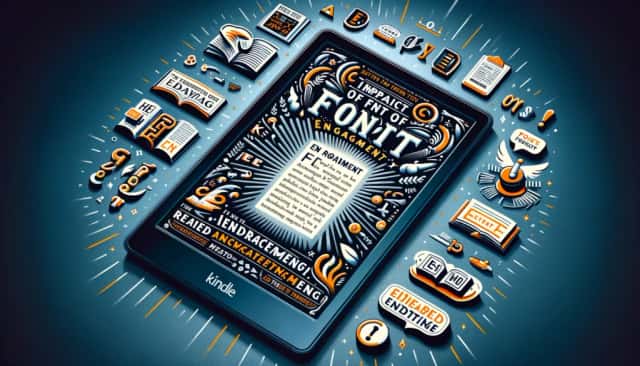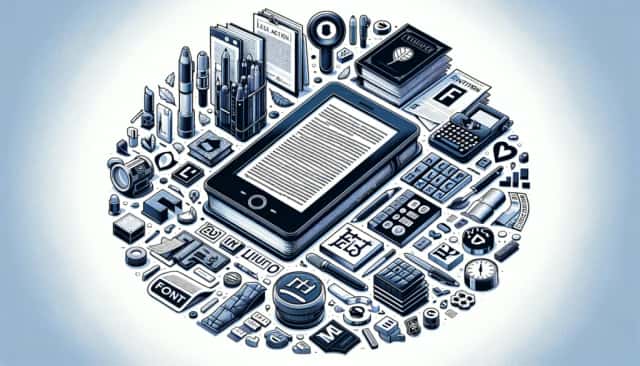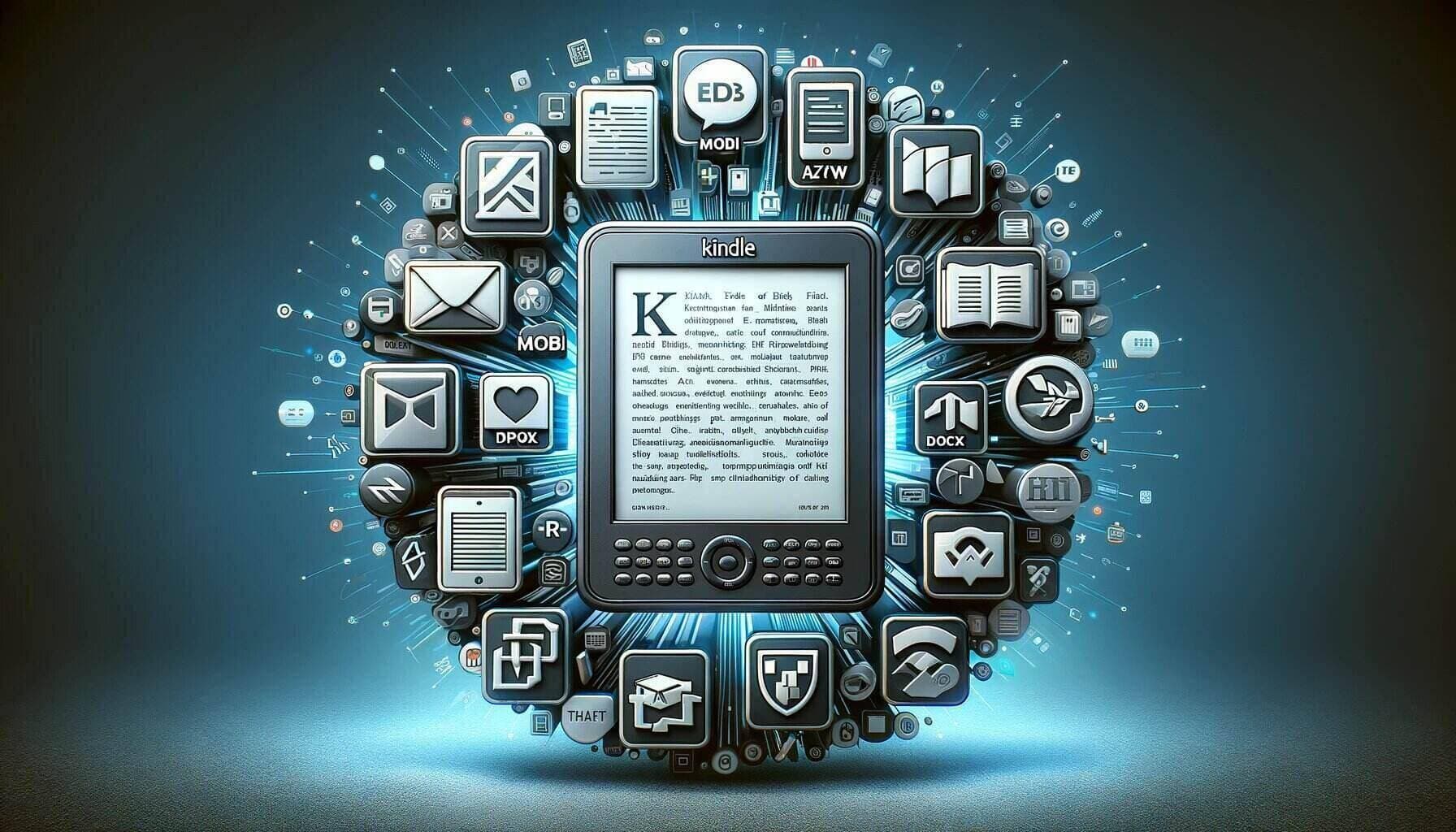
Hast du jemals darüber nachgedacht, wie die beste Schriftart für Kindle dein Leseerlebnis erheblich beeinflussen kann? Es ist etwas, dem nicht viel Beachtung geschenkt wird, aber glaub mir, es ist bahnbrechend. Die Wahl der richtigen Schriftart geht nicht nur um Ästhetik; sie geht um Komfort, Lesbarkeit und darum, dass deine Augen nicht zu schnell ermüden.
Wenn du die perfekte Schriftart findest, scheint es, als würden die Wörter einfach fließender fließen, wodurch deine Lesesitzungen noch angenehmer werden. Und wenn du für Kindle schreibst und veröffentlichst, wird diese Wahl noch entscheidender. Du willst, dass deine Leser ohne Anstrengung in deine Geschichten eintauchen, gefesselt und bequem bleiben.
Also lass uns herausarbeiten, warum die Wahl der perfekten Schriftart wichtig ist und wie sie dein Kindle-Erlebnis sowie das deiner Leser verstärken kann. Stell es dir als eine von diesen kleinen Anpassungen vor, die große Vorteile bringen – etwas, von dem ich mir gewünscht hätte, es zu wissen, als ich meine Kindle-Reise begann.
Beste Schriftart für Kindle
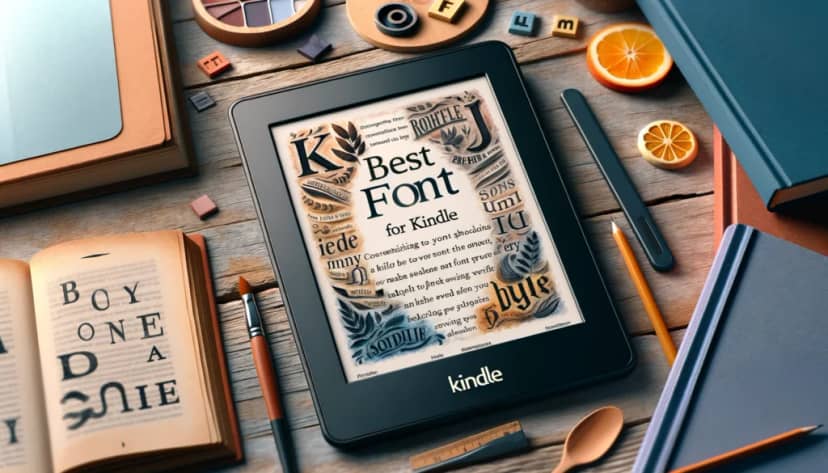
Die Wahl der besten Schriftart mag trivial klingen, doch sie ist mehr als nur das Aussehen der Buchstaben. Denken wir kurz darüber nach, warum die Schriftart wichtig ist, und schauen uns dann einige der beliebtesten Optionen an.
Warum die Schriftart beim Kindle-Lesen wichtig ist
Zuerst lass uns über Komfort sprechen. Das Lesen auf einem digitalen Bildschirm ist nicht dasselbe wie das Umblättern durch die Seiten eines Taschenbuchs. Unsere Augen arbeiten anders, wenn wir auf einen beleuchteten Hintergrund starren.
Hier kommt eine gute Schrift ins Spiel. Die richtige Schrift kann die Augenbelastung verringern und es dir leichter machen, dich stundenlang in ein Buch zu vertiefen, ohne das Gefühl zu haben, dass deine Augen gleich protestieren.
Dann kommt die Frage der Lesbarkeit. Nicht alle Schriftarten sind gleich geschaffen – manche sehen auf einer Seite hübsch aus, können aber zu einem kleinen Albtraum werden, wenn man ihnen Zeile für Zeile auf dem Bildschirm folgen möchte.
Kindle-Bildschirme sind ziemlich gut, aber sie sind nicht perfekt, und manche Schriftarten funktionieren in dieser digitalen Umgebung einfach besser. Sie helfen, den Text klar und scharf zu machen, sodass du nicht zusammenkneifen oder die Helligkeit alle paar Minuten anpassen musst.
Und hier ist etwas, das nicht jeder in Betracht zieht – die Stimmung. Ja, Schriftarten tragen eine Atmosphäre in sich! Denke darüber nach: Ein Thriller wirkt vielleicht nicht so bedrückend in einer Comic Sans-ähnlichen Schrift, oder?
Deine Schriftwahl kann tatsächlich den Ton deines Buches ergänzen und dem Leser eine zusätzliche Atmosphäre hinzufügen.
Wenn du durch die Schriftoptionen auf deinem Kindle scrollst oder dein Manuskript für die Veröffentlichung vorbereitest, erinnere dich daran, dass es nicht nur eine triviale Entscheidung ist. Es geht darum, dein Lese- oder Schreiberlebnis so angenehm und effektiv wie möglich zu gestalten. Glaub mir: Sobald du anfängst, darauf zu achten, wirst du sehen, dass es wirklich eine echte Veränderung ist!
Beliebte Schriftarten für Kindle
Bevor man sich in bestimmte Schriftarten vertieft, ist es hilfreich zu wissen, dass es zwei Haupttypen gibt: Serif und Sans Serif.
Serif-Schriften haben kleine Linien an den Enden der Buchstaben und vermitteln ein traditionelles Erscheinungsbild. Sans-Serif-Schriften, denen diese Linien fehlen, wirken sauberer und moderner.
Beide Typen haben ihre Vorteile beim Kindle-Lesen.
Serif-Schriften
Serif-Schriften werden oft mit Komfort und Leichtigkeit beim Lesen längerer Texte in Verbindung gebracht, dank ihres traditionellen Erscheinungsbildes und der Art, wie die Serifen das Auge des Lesers von einem Wort zum nächsten führen.
- Bookerly: Amazons eigene Kreation, speziell für Kindle-Geräte entwickelt, und bietet eine optimale Balance zwischen Ästhetik und Lesbarkeit.
- Georgia: Bekannt für ihre Lesbarkeit auf Bildschirmen, Georgia verfügt über eine großzügige x-Höhe, was sie auch bei kleineren Größen klar und gut lesbar macht.
- Times New Roman: Eine klassische Schriftart, die zwar traditioneller ist, vielen Lesern aber vertraut ist und bequem auf Kindle-Geräten verwendet werden kann.
Sans-Serif-Schriften
Sans-Serif-Schriften sind typischerweise leichter für die Augen beim Lesen am Bildschirm und bieten ein geradliniges, sauberes Erscheinungsbild, das die Augenbelastung minimiert.
- Verdana: Entwickelt mit dem Lesen auf dem Bildschirm im Sinn; seine breiten Buchstaben und großzügige Abstände machen es zu einer soliden Wahl für Kindle-Nutzer.
- Arial: Bekannt für Klarheit und Einfachheit, ist Arial eine vielseitige Schriftart, die auf digitalen Bildschirmen gut lesbar ist.
- Helvetica: Bekannt für ihre Neutralität und Lesbarkeit, ist Helvetica eine beliebte Wahl über verschiedene digitale Plattformen hinweg, einschließlich Kindle.
Wie man die beste Schriftart für Kindle testet und auswählt
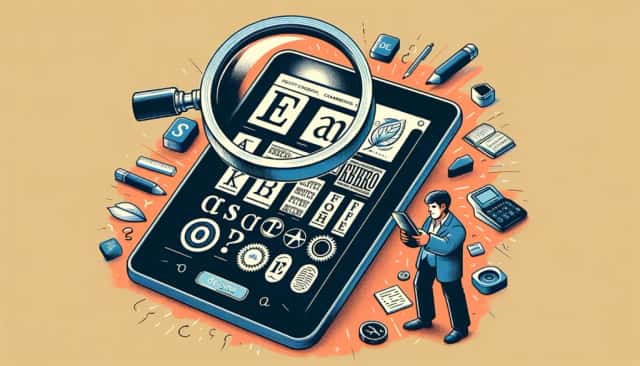
Welche Schrift ist am besten für E-Books geeignet?
Die beste Schrift für E-Books balanciert Lesbarkeit und Ästhetik. Schriftarten wie Bookerly, Georgia und Verdana sind beliebte Optionen, die eine breite Palette von Lesepräferenzen und Geräten bedienen.
Beste Kindle-Schriftart bei ADHS?
Für Leser mit ADHS sind Schriftarten, die die Konzentration und Lesbarkeit erhöhen, ohne abzulenken, ideal. Arial und Verdana sind gute Optionen aufgrund ihres klaren, einheitlichen Erscheinungsbildes, das dabei helfen kann, die Konzentration aufrechtzuerhalten.